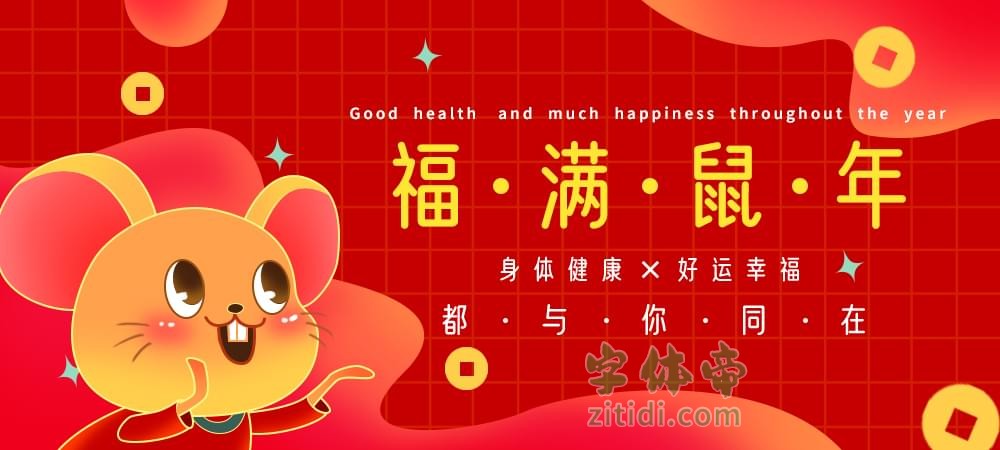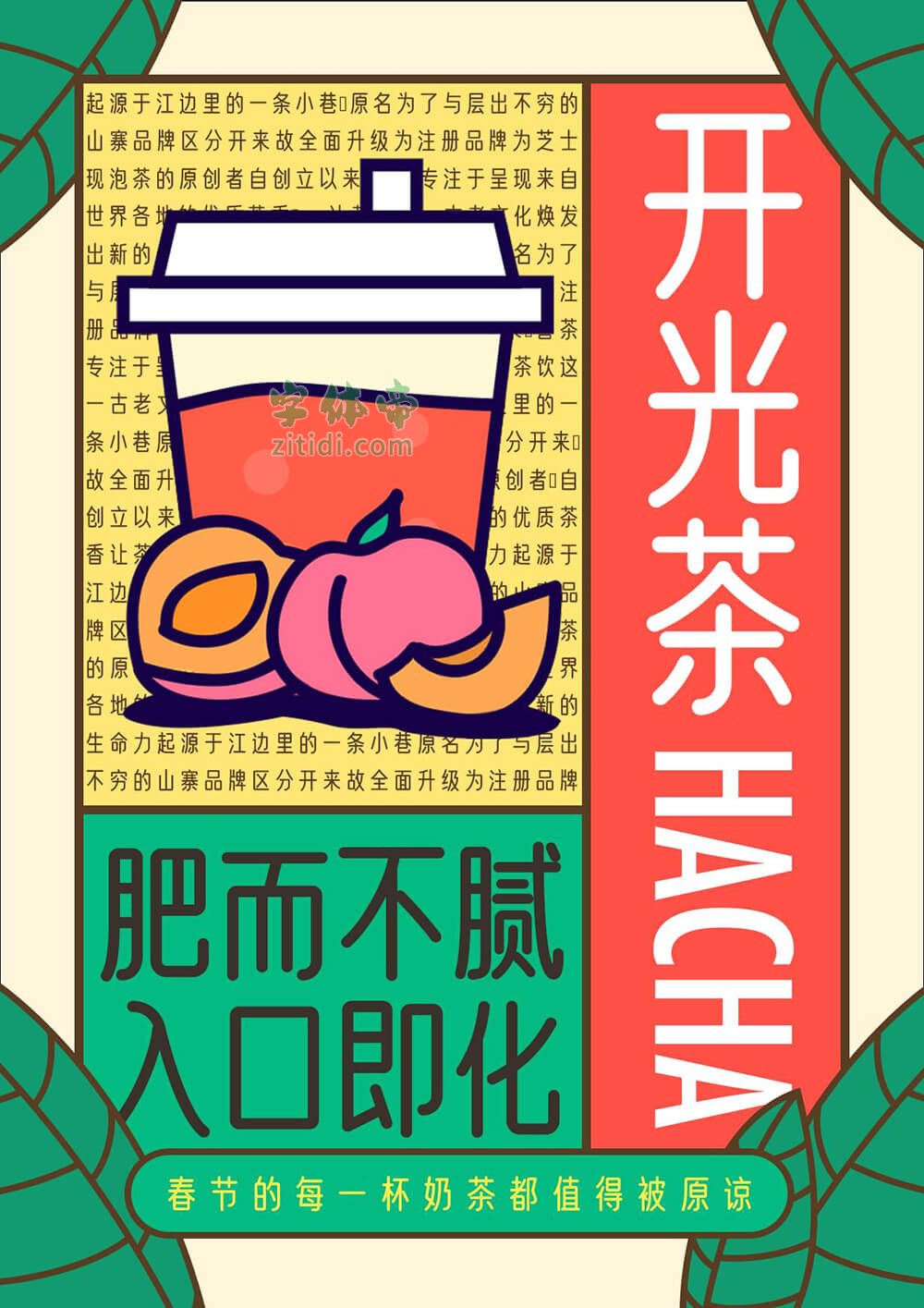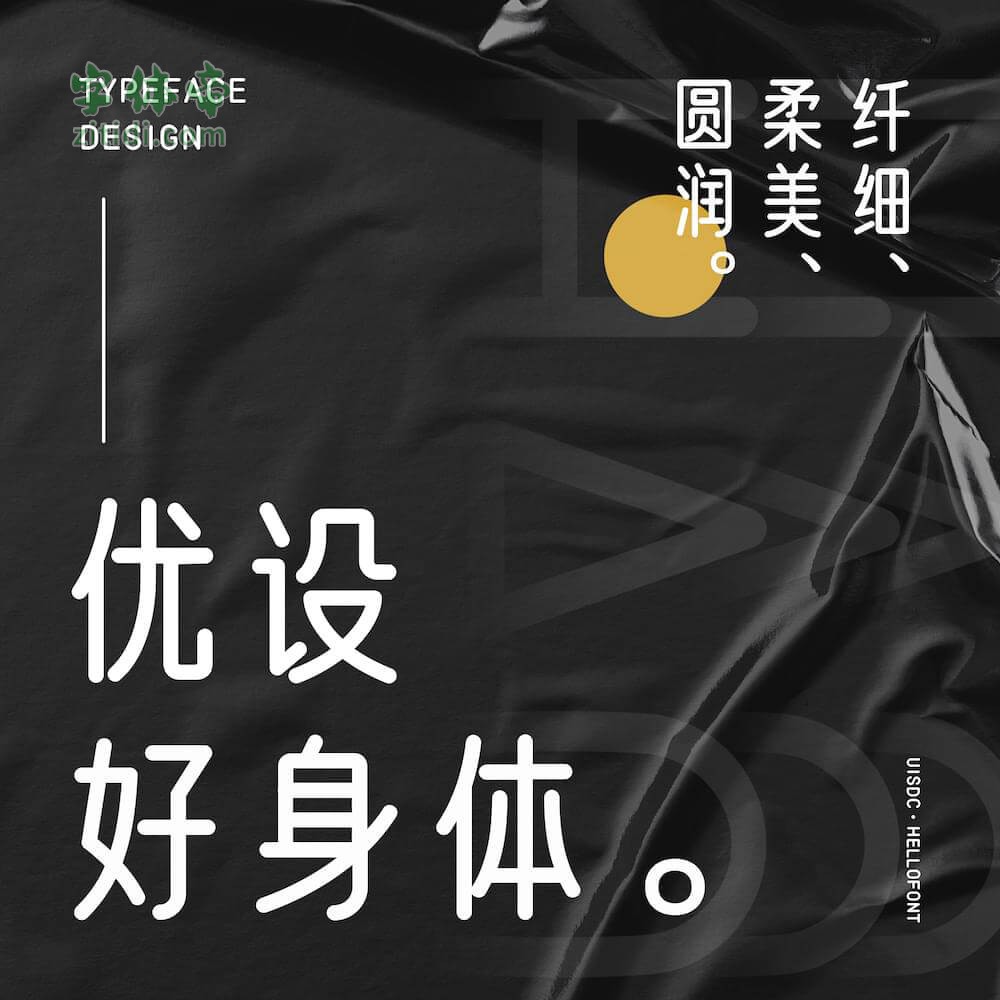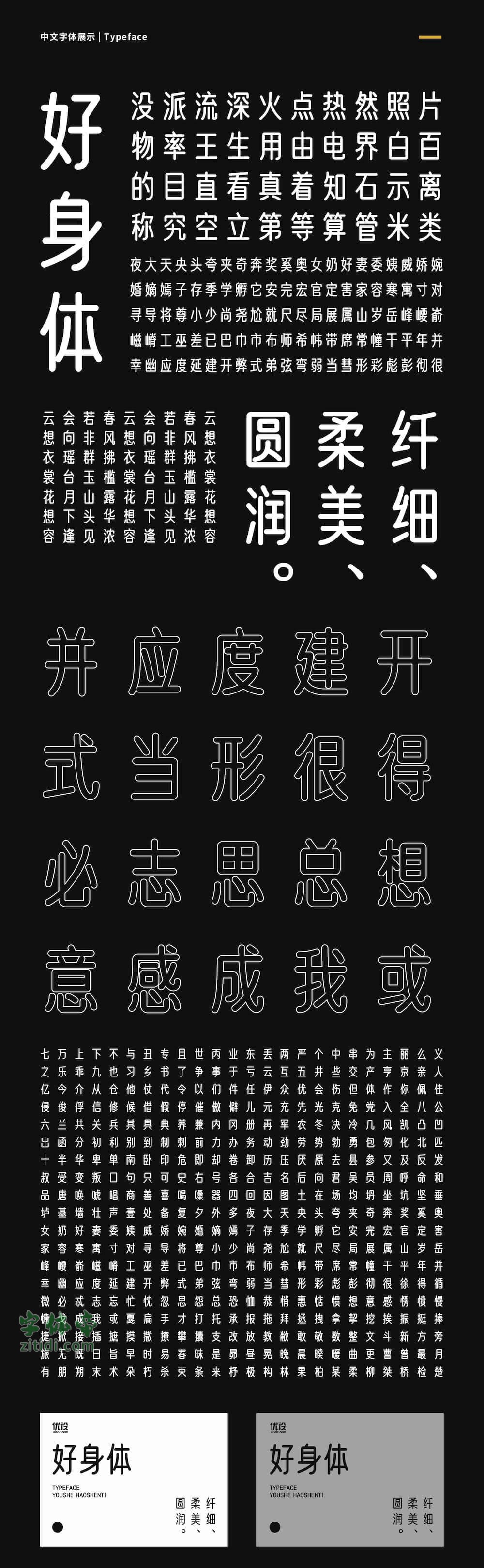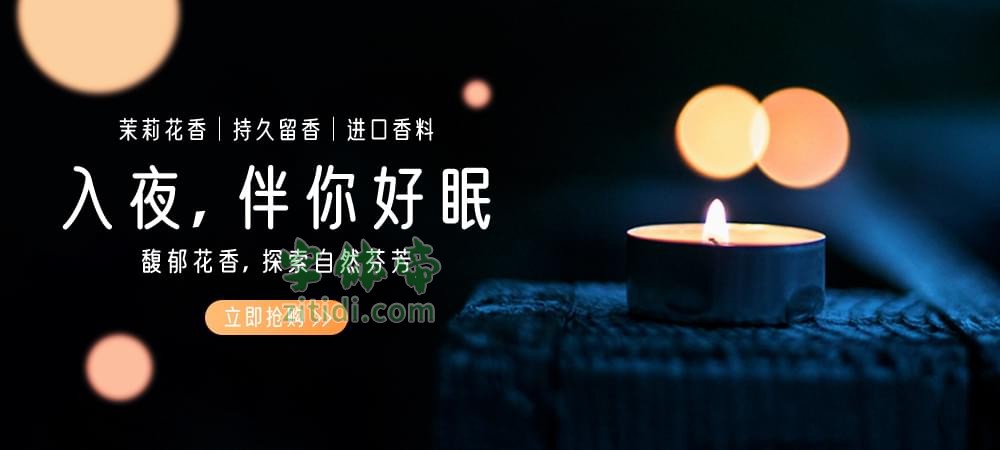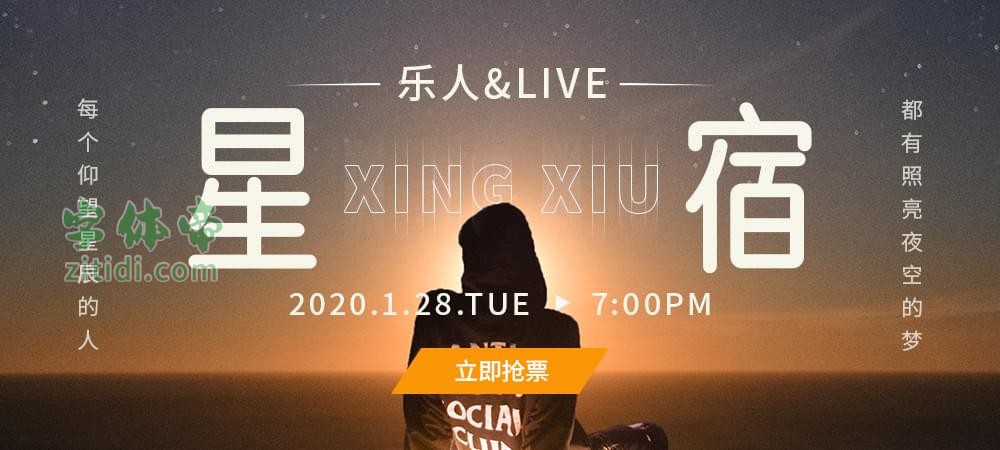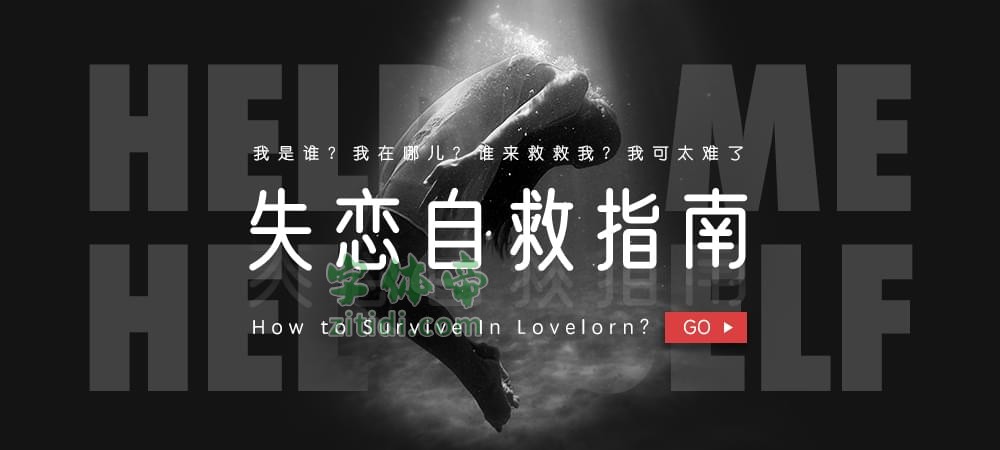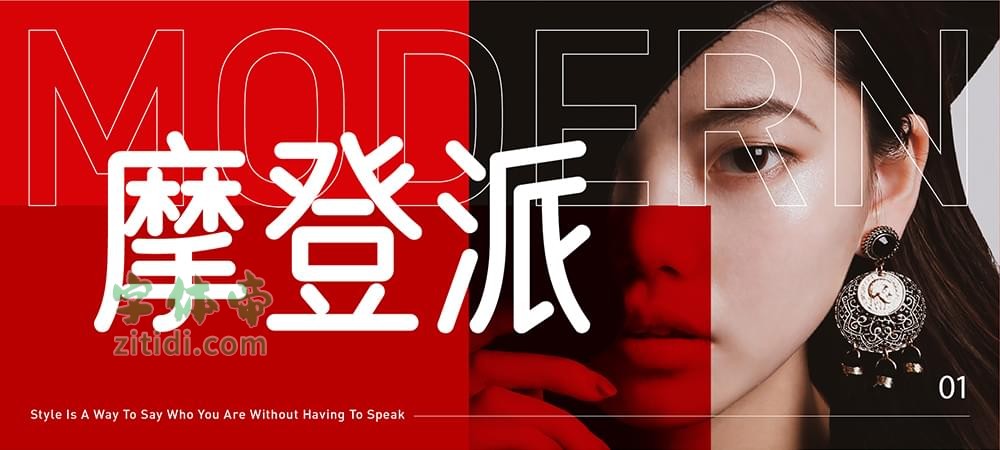
需要强调的是,这款字体的命名和风格去年 10 月份就定下来了。 优设(浪漫的)初衷是希望设计师们用了这款字体,能减少改稿的次数,少点熬夜有个好身体。现在遇上疫情,更是成为我们对每个人的祝福,希望大家都像这款字体名字一样,平平安安有个好身体!
用过优设标题黑的设计师肯定记得,那是一款兼具速度感和力量感,沉稳有力的标题字。而优设好身体恰恰和它截然不同,一个扁平一个瘦高,一个刚猛一个温柔,设计师笑称“它俩是一对”。
优设好身体是一款亲和力、现代感极强的专业美术标题字体。它以圆体字型为基础,通过瘦高的字面、偏向几何的曲线,让整宽字体富有亲和力和时尚感。在同样的面积里,更窄的字面就意味着能容纳更多的信息,所以这款字体非常适用在需要体现亲和力与时尚感的各类品牌宣传广告和产品包装设计的标题上。
“优设好身体”是一款书写很新颖的字体,字体大方,适合各种设计作品使用!欢迎下载!